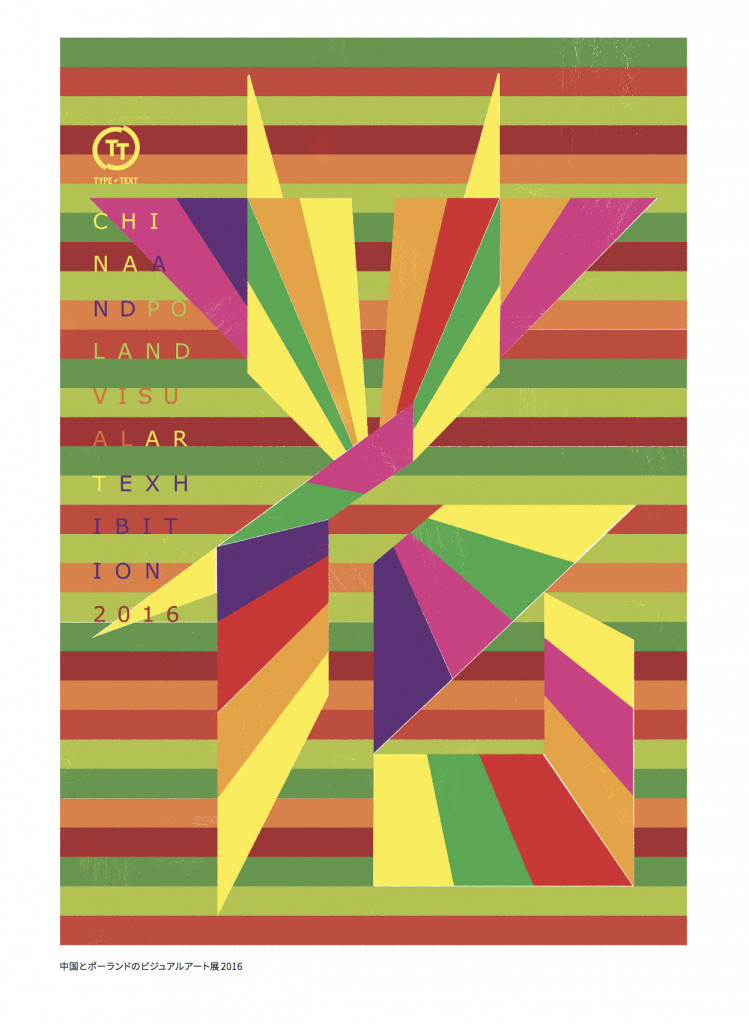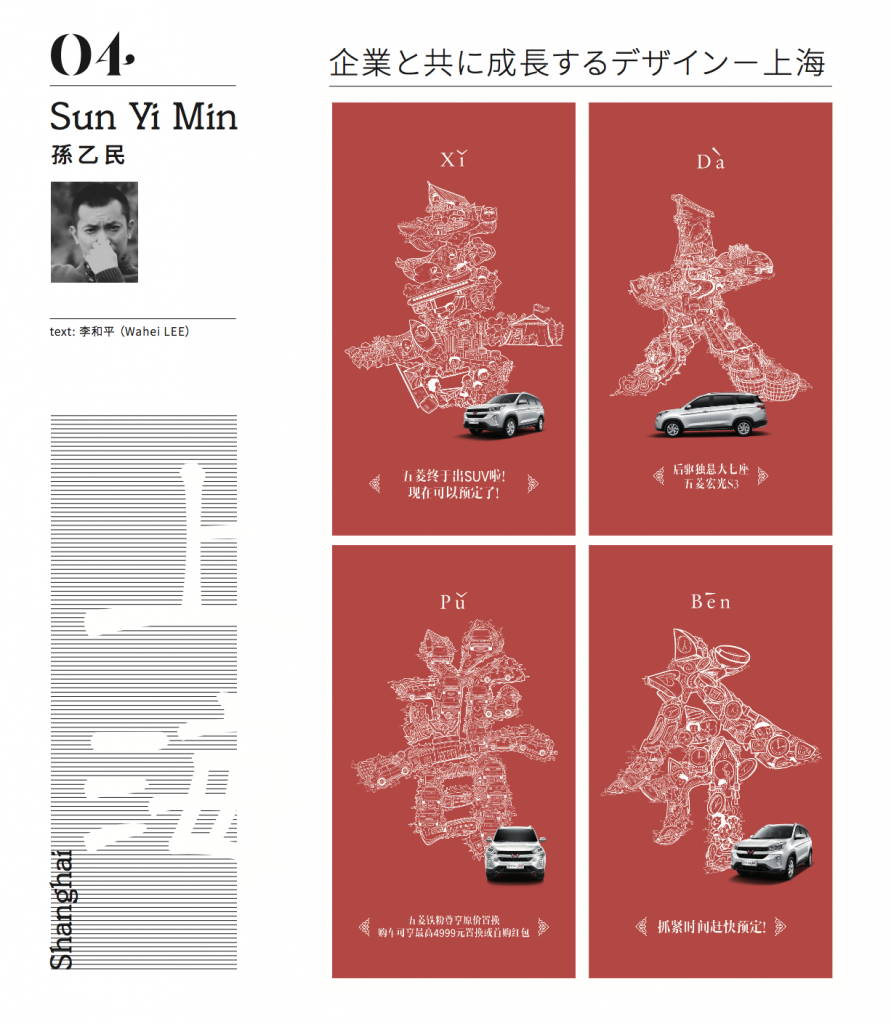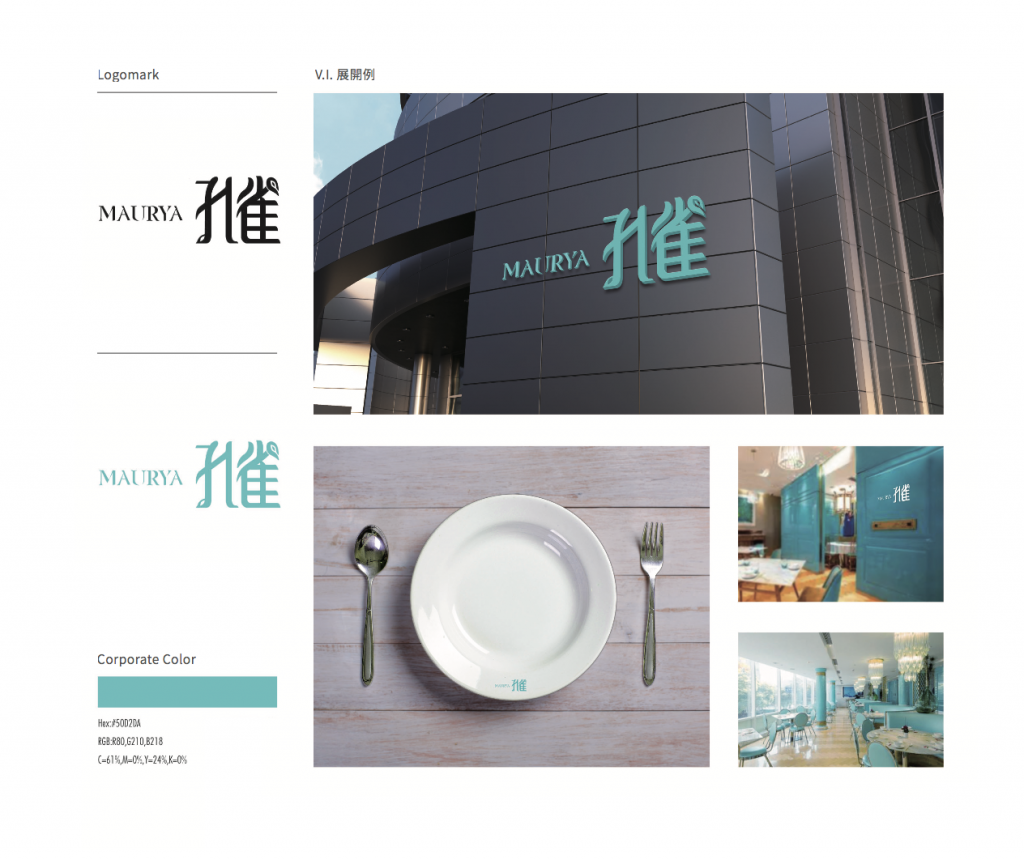
t誌291号特集は、「アジア発信のデザイナー」。
香港、台湾、深圳、上海。歴史も発展過程も異なるアジアの都市を拠点に活躍する4人のデザイナー。彼らが住む街でのデザインの取り組みについて話をうかがった。
本ページでは、香港「陳超宏」氏、上海「孫乙民」氏インタビューの一部を紹介する。
「香港のデザインの魅力」を教えてください。
個人的には70年代、80年代の香港デザインが好きです。当時はさまざまな分野のデザインが一斉に開花し、まさに百花繚乱の時代でした。
当時、経済は確実な成長を続け、多くの産業からデザインの需要がありました。たくさん外国人デザイナーが香港に移住し、デザイン・スタジオを開設しました。
当時は香港の学生やデザイナーが西洋のデザインを学び、意見交換することができました。東洋と西洋が出会う「るつぼ」の中で多国籍デザインが誕生しました。
「香港のタイポグラフィ」についてのお考えをお聞かせください。
香港は歴史的に英国の植民地だったことや、中国からの移民など、東洋文化と西洋文化が出会う場として他にない特徴があります。
それによって香港のデザイナーはバイリンガルな活字開発の訓練ができています。都市を歩いていると、 いつも東洋と西洋が混じった複雑な多国籍二か国語のデザインや道路標識といった独特の記号を目にします。
今後も東洋と西洋が合体したデザイン、特に二か国語タイポグラフィで香港のデザインの興隆は続くと思います。
陳超宏 プロフィール
Eric Chan Design Co. Ltd.
香港出身。香港理工大学と大一エリック・チェン美術学校卒業。1991年、Eric Chan Design Co. Ltd. を設立。
アメリカ ONE Show「デザイン金賞」、イギリス D&AD「イエロー・ペンシル・ノミネート推薦賞」、日本タイポグラフィ協会「年度最優秀賞」、香港デザイナー協会「デザイン金賞」など、香港や国際大賞を多数受賞。
「上海のデザイン」についてのお考えをお聞かせください。
タイポグラフィのグラフィックデザイン表現については、西欧の表音文字(英字)と東洋表意文字(漢字)の両者は根本的に異なると思います。
単体の表音文字の意味は存在しないと考えます。しかし、単体の表意文字(漢字)はデザイン性プラス感情的なカラーや意味合いがあると思います。
この両者を絡めて構成する(デザインする)のはやりがいのある事だと思います。
上海にいるデザイナーやアートディレクターなどは世界各国(地域)の人間から構成され、これからは国際都市として世界に通用するデザインが増えるでしょう。
その中で漢字と英文、漢字と日本語、漢字のイメージ、図柄への表現が次々と街に現れると思います。中国人デザイナーとして、求知のこころを忘れずに上海の素敵な都市創りに貢献するつもりです。
「上海のデザインがどのように発展する」と考えてますか?
今の上海ではデザインをやりすぎる事がある。要するに全てをデザインで表現しようとするとアイデアが少なくなるはずです。
新鋭デザイナーは必ず新しい事を吸収し、自分自身と新時代の複合のような人間になろうとする決意が必要でしょう。
中国の中でも上海は外国人の租界という時代があり、異文化を受入れる度量がある。これからの上海デザインは間違いなく国際的に通用するデザインになるでしょう。
孫乙民 プロフィール
Sun Yi min ソン・イーミン
1978年生まれ。西安美術学院芸術デザイン学科を卒業後、上海WPG伙伴集団に勤務、クリエイティブ総監として活動。2002年より上海で16年間上海広告業で活躍。
広告グラフィックデザインやタイポグラフィを得意とする。中国広告業の受賞歴がある。非常にハングリー精神が強く、次 世代を担う人物として期待されている。